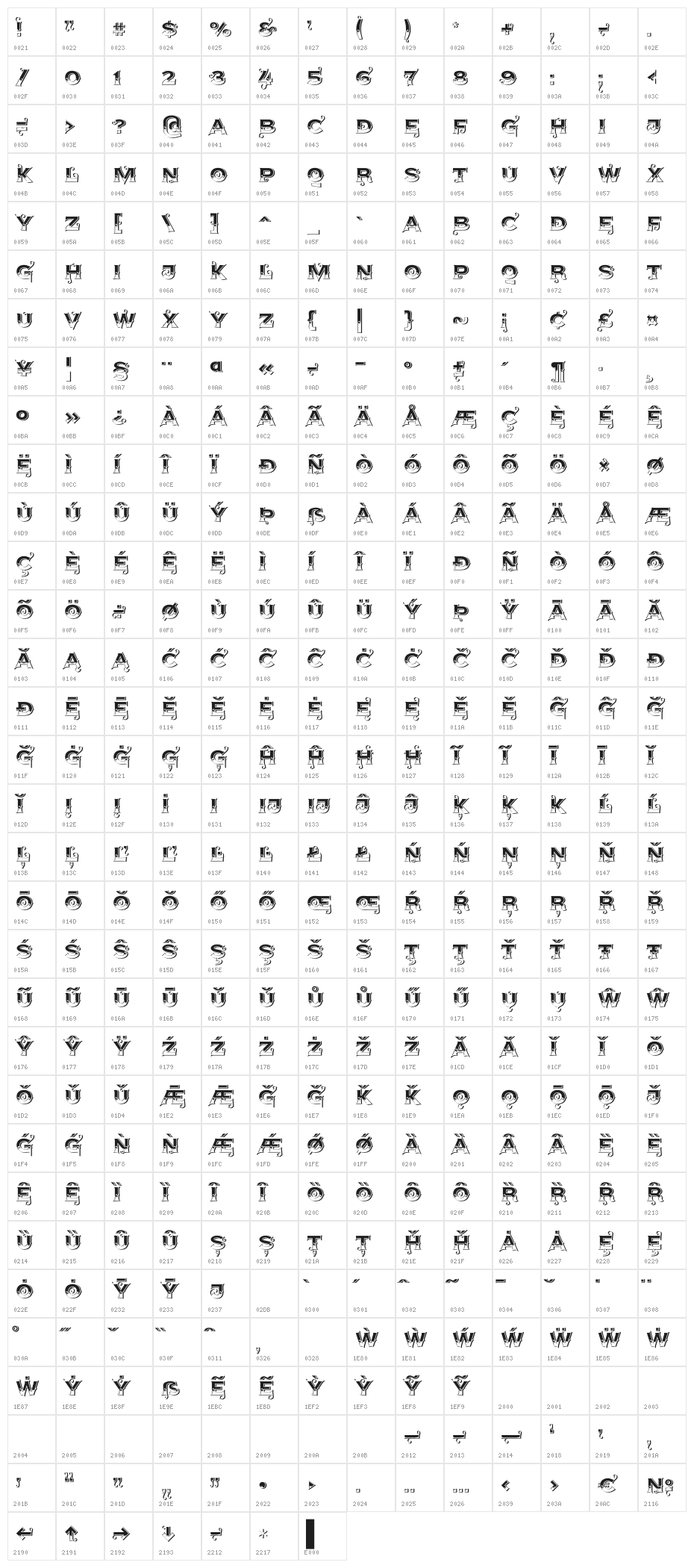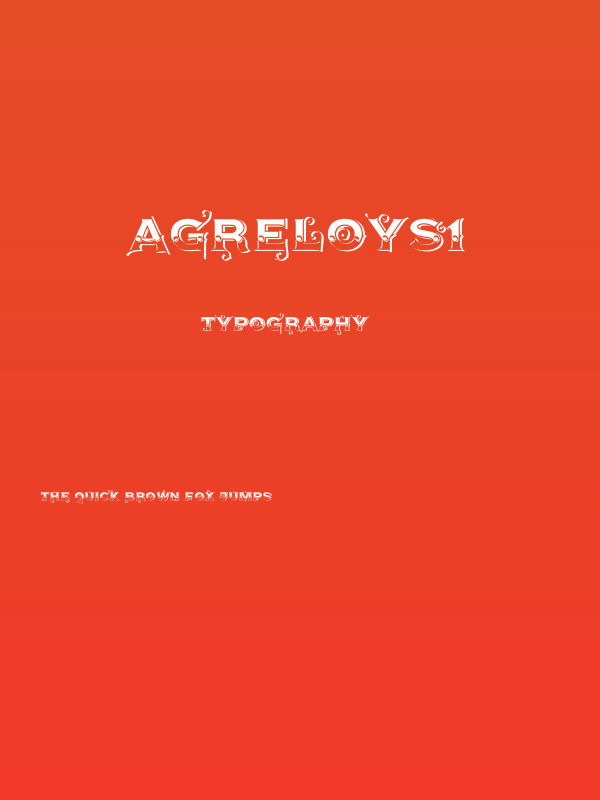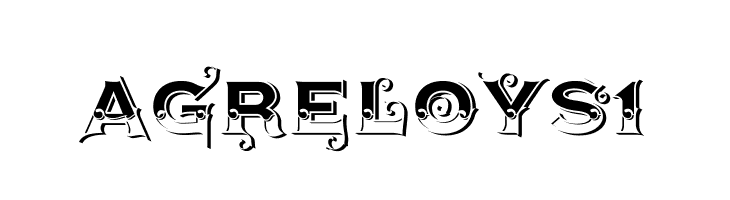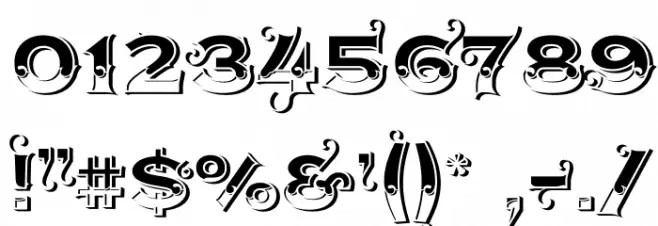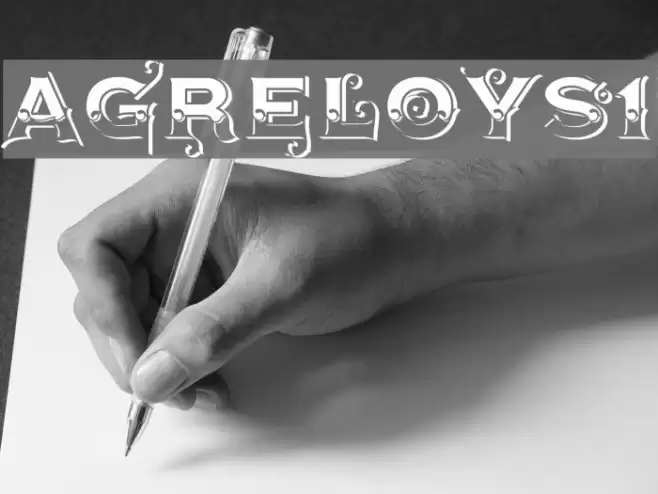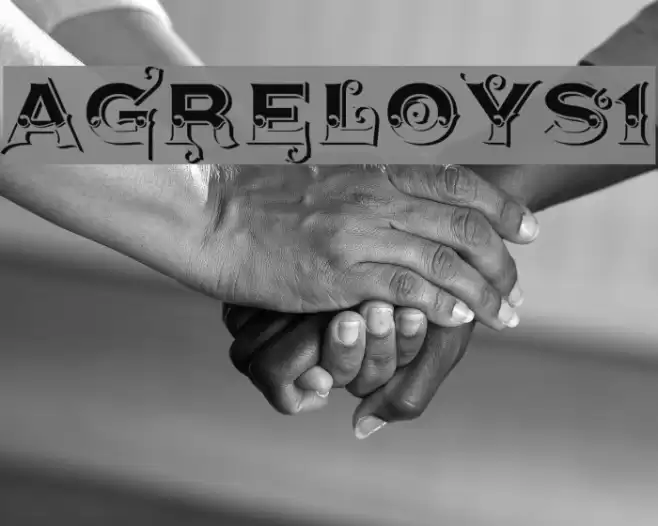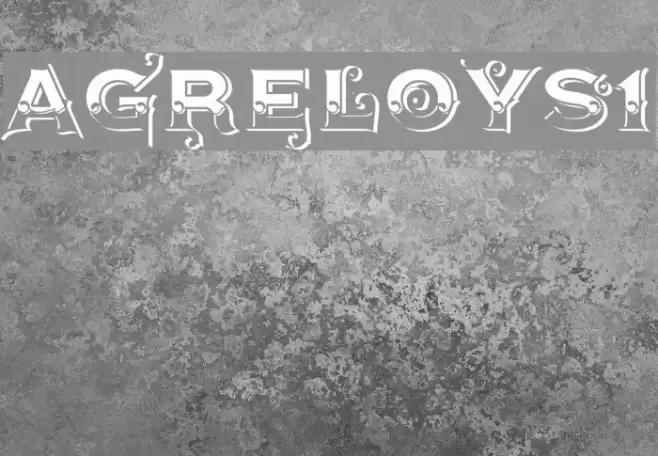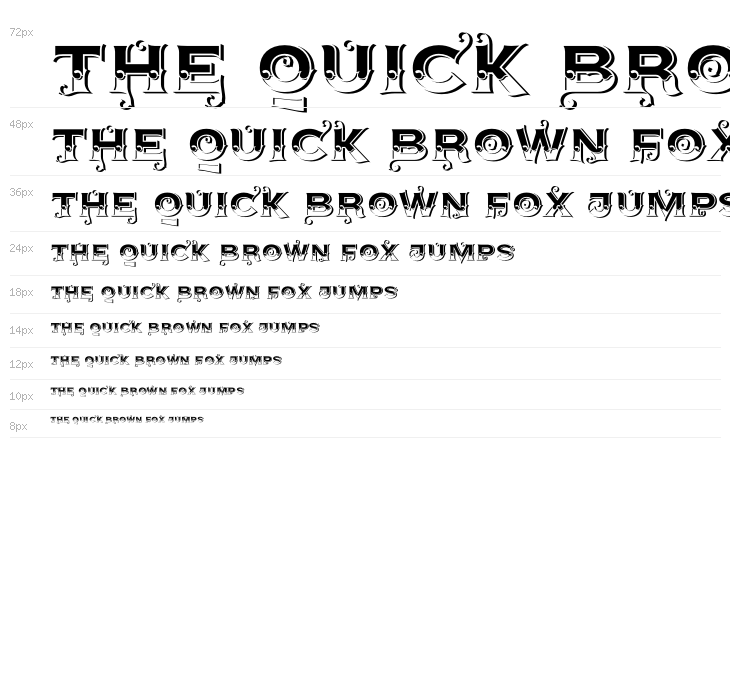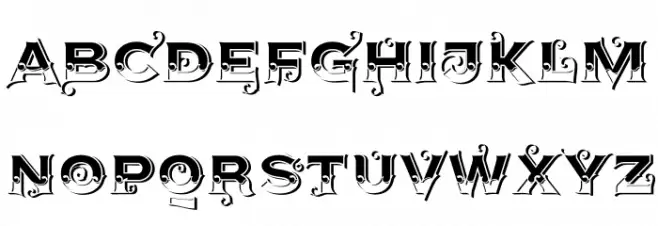
AgreloyS1 Font
✎ Curly
| 用途 | Logos, Headlines, Decorative text |
| おすすめプロジェクト | Ideal for wedding invitations, vintage-themed posters, branding for luxury products, and decorative signage. |